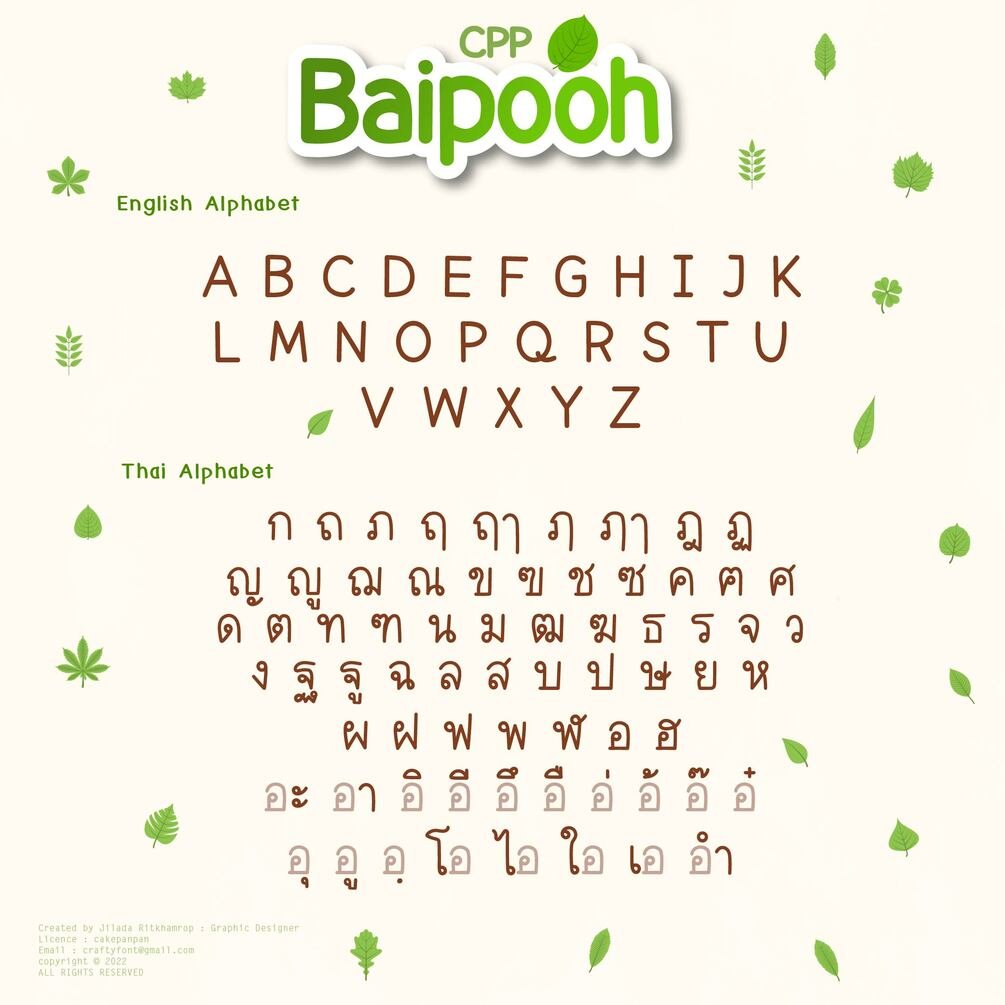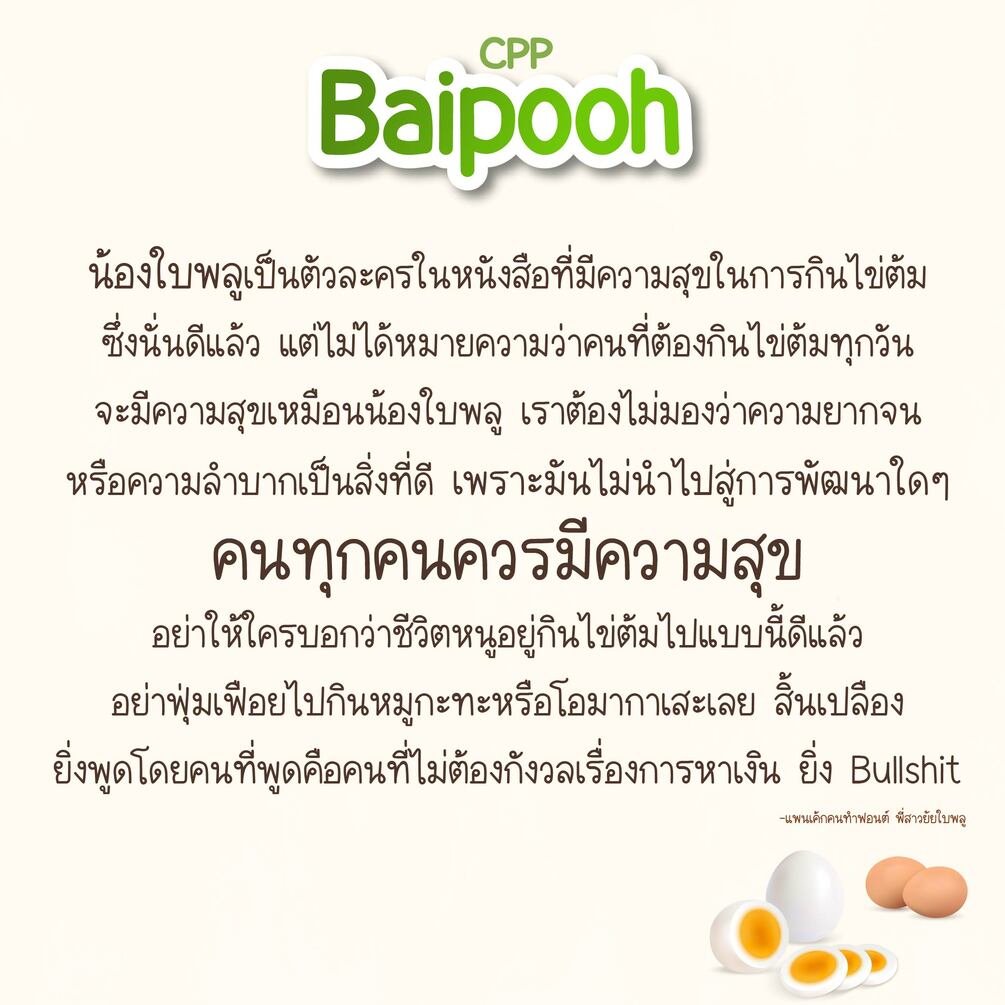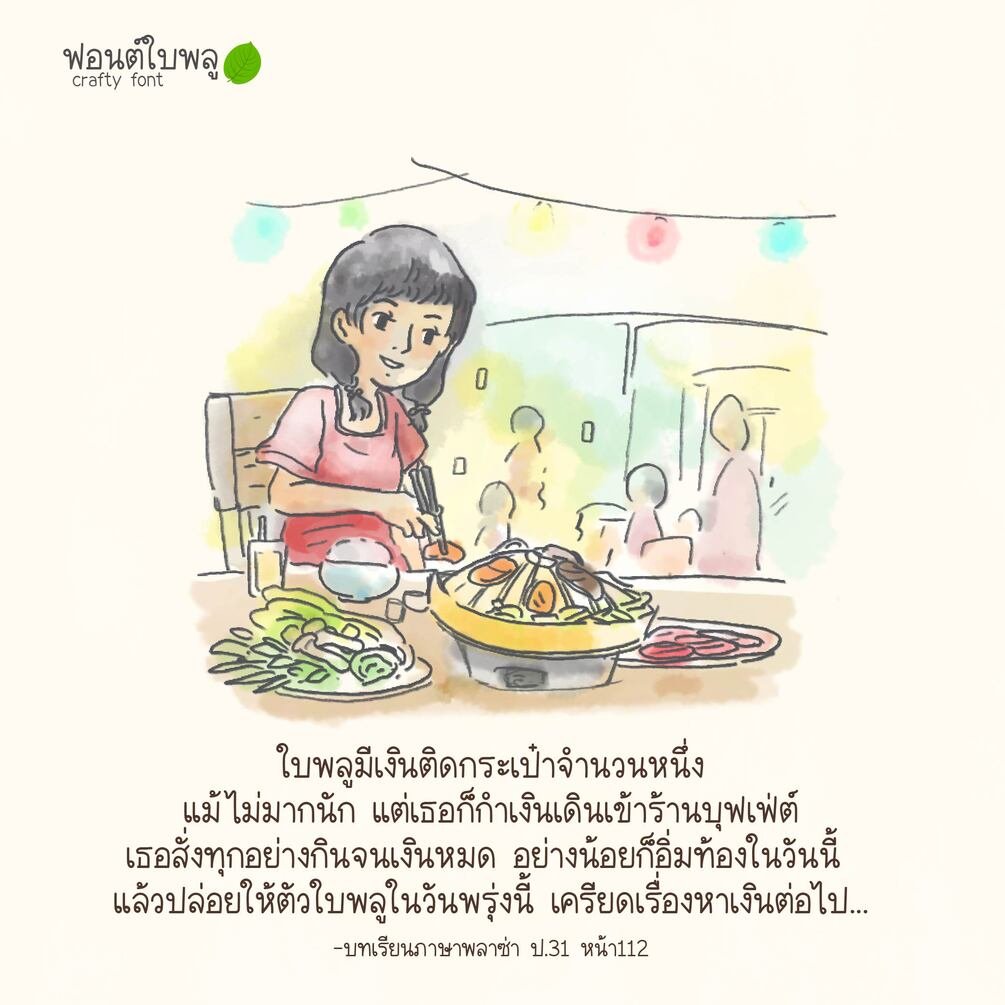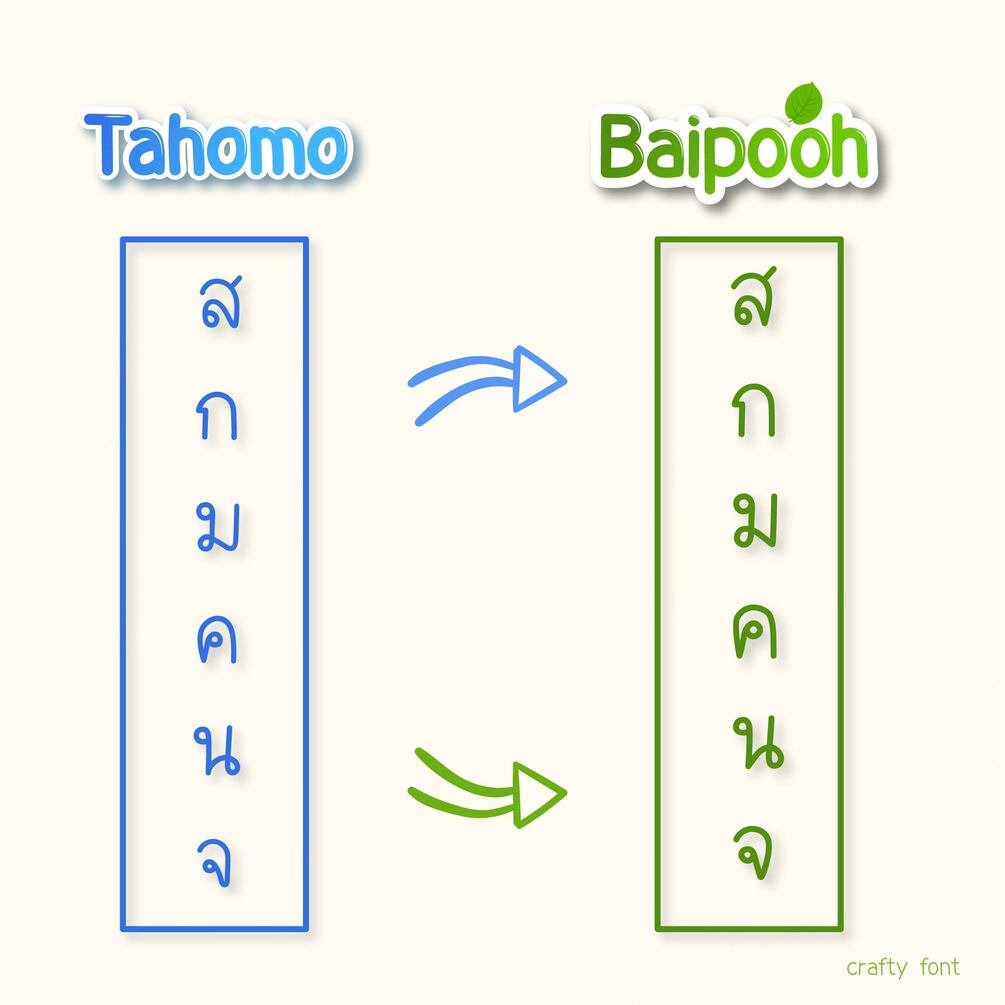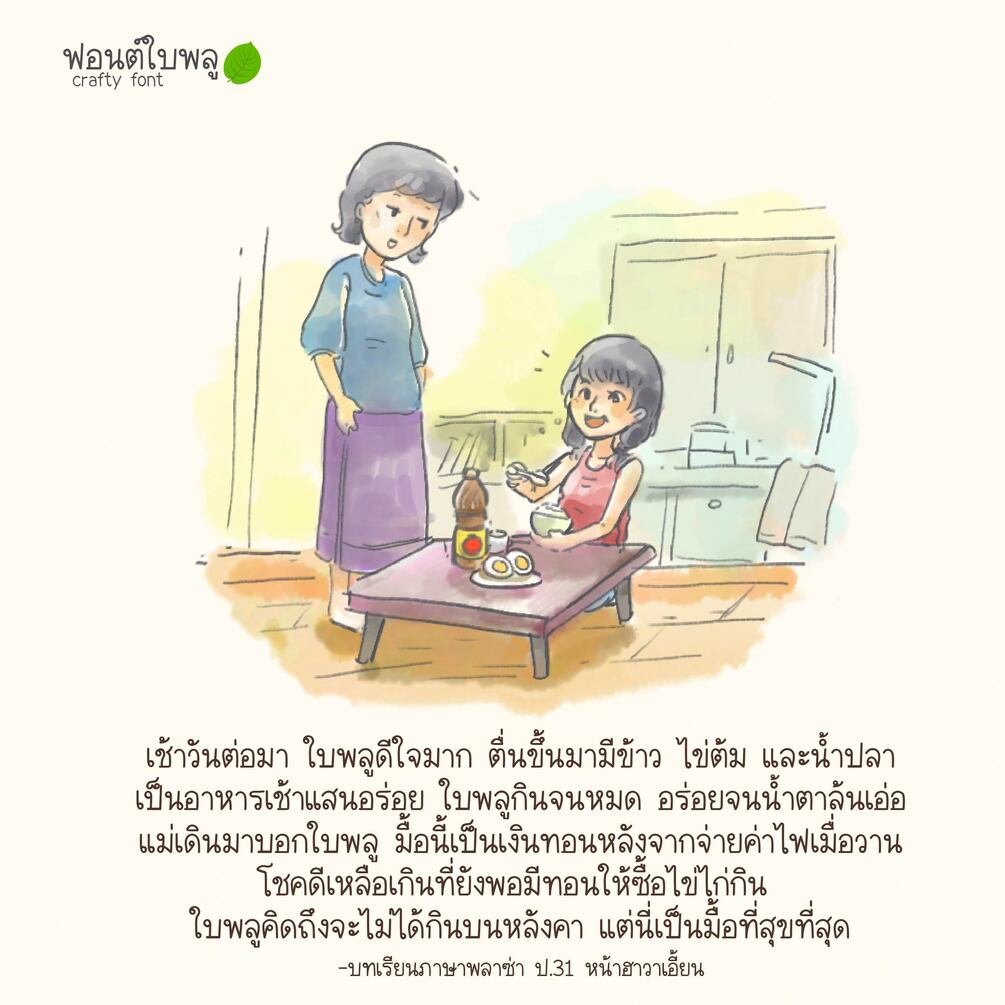
CPP Baipooh Font (ฟอนต์ซีพีพี ใบพลู)
ฟอนต์ซีพีพีใบพลู (CPP baipooh) พัฒนามาจากฟอนต์ทาโฮโมะ (Tahomo Font) ที่ปล่อยไปเมื่อ 3 ปีก่อน เอามาแก้ไขข้อบกพร่องต่างๆ ให้แสดงผลได้สมูธมากยิ่งขึ้น 😄😄 ใช้ทำคอนเทนต์ก็ปัง เหมาะกับการจดโน๊ตมาก ช่วยให้จำเนื้อหาได้ดีขึ้น 😎😎